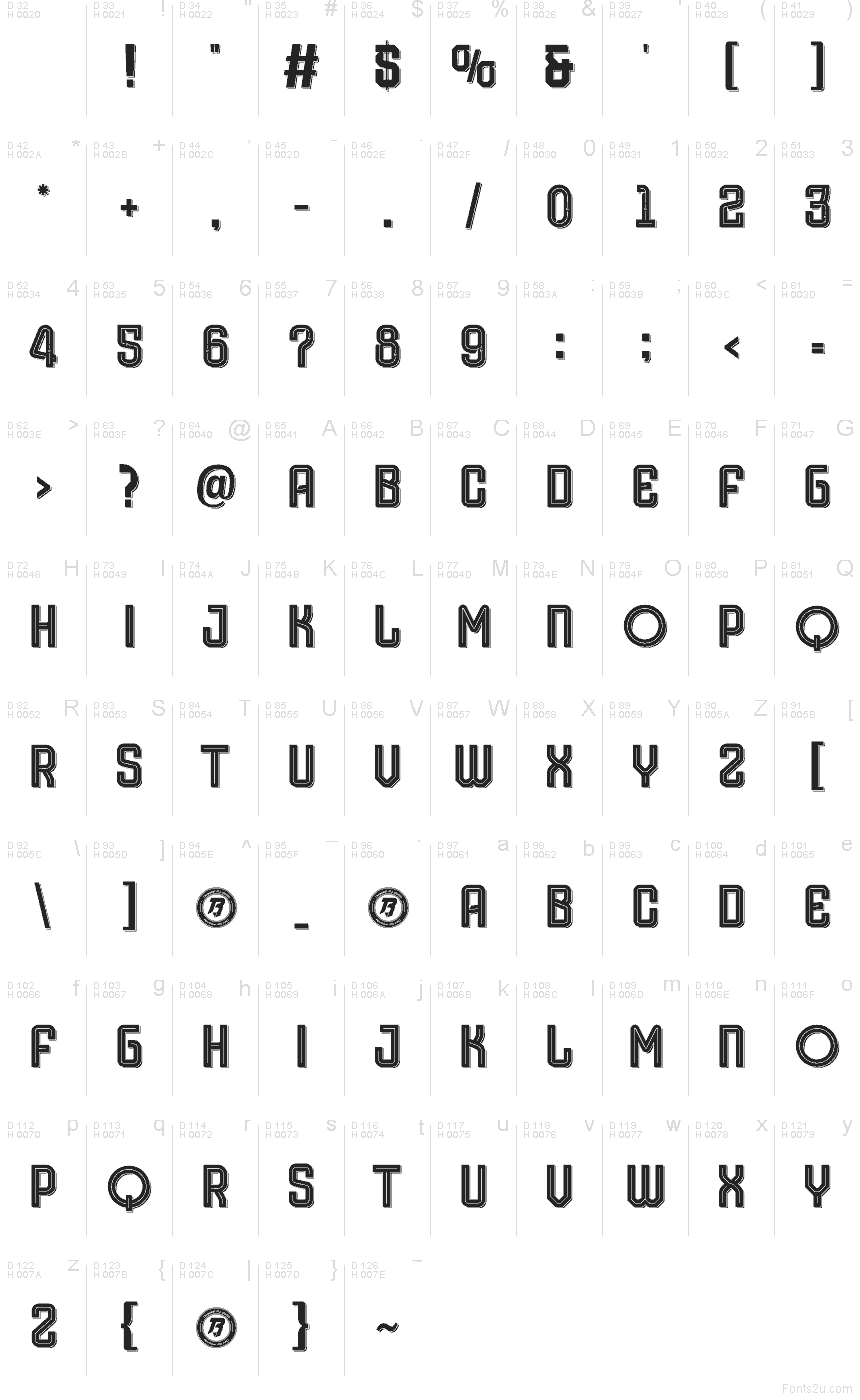
Il font Eindhoven VIII di Muhammad Afif Ersya di Trequartista Studio è un carattere techno gratuito caratterizzato da un elegante profilo a doppia linea, che ricorda i tubi al neon collegati a un circuito stampato. Il suo ritmo alto e condensato, unito agli angoli netti, conferisce ai titoli un battito veloce e tecnologico, mentre le linee interne aperte donano leggerezza al design.
Usa Eindhoven VIII per dare un impatto deciso a grafiche per esports e gaming, poster sci-fi, volantini di eventi tech, banner web, copertine di album, packaging di prodotti e loghi futuristici. Usalo in grande formato lasciando un po' di respiro; abbina questo font gratuito a una sans-serif geometrica pulita per il testo principale, così i dettagli dei contorni rimarranno protagonisti.